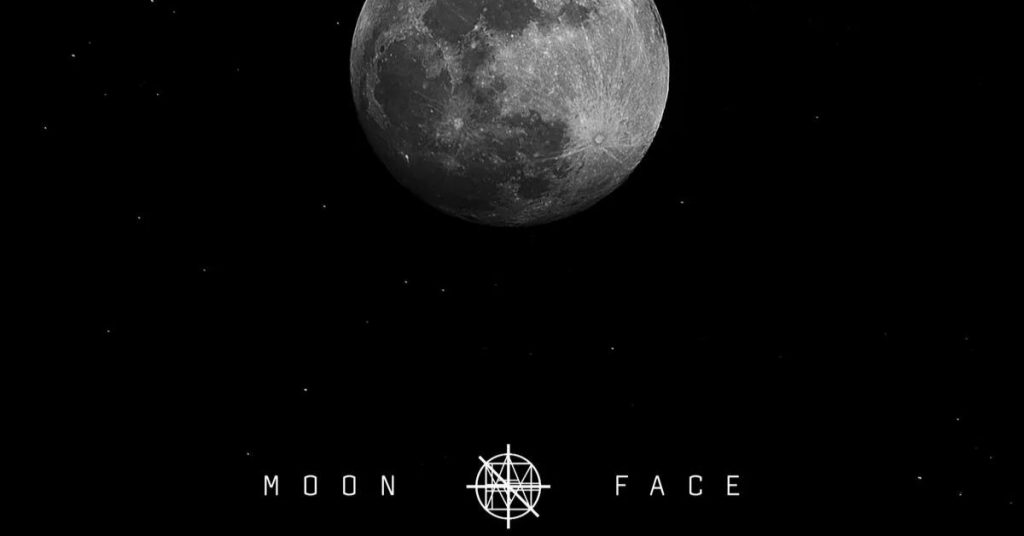
L’agence FRED & FARID Shangaï rend hommage à l’unique satellite permanent de la Terre : la Lune. Comment ? En lui dédiant une police d’écriture. Baptisée “MoonFace”, cette dernière s’inspire de la forme mais aussi de la rotation de ladite sphère.
“MoonFace” : la police d’écriture en hommage à la Lune
The Moon Festival, aussi connue sous le nom de Lunar Festival ou Mid-Autumn Festival ; est profondément ancré dans l’histoire ancestrale de la Chine. Cette année, il fut célébré le 21 septembre dernier (soit le 15e jour du huitième mois lunaire) : la pleine lune la plus brillante de l’année.
Ce jour phare est aussi symbole d’unité et de résilience. C’est pourquoi, l’agence FRED & FARID Shanghaï a souhaité mettre en lumière cette tradition et ces valeurs, à sa façon. Pour ce faire, elle a dévoilé “MoonFace”.
Inspirée par la forme et la rotation de la Lune, “MoonFace” se compose de 26 lettres, 10 chiffres et 20 ponctuations. Chaque lettre est entourée d’un cercle pour indiquer l’état du cycle de la Lune. L’axe changeant est une représentation de sa rotation et des angles infinis qui la sous-tendent.
Une façon poétique de rappeler que, tout comme la Lune, nous avons aussi le pouvoir de changer et de nous transformer dans un monde en perpétuel mouvement.